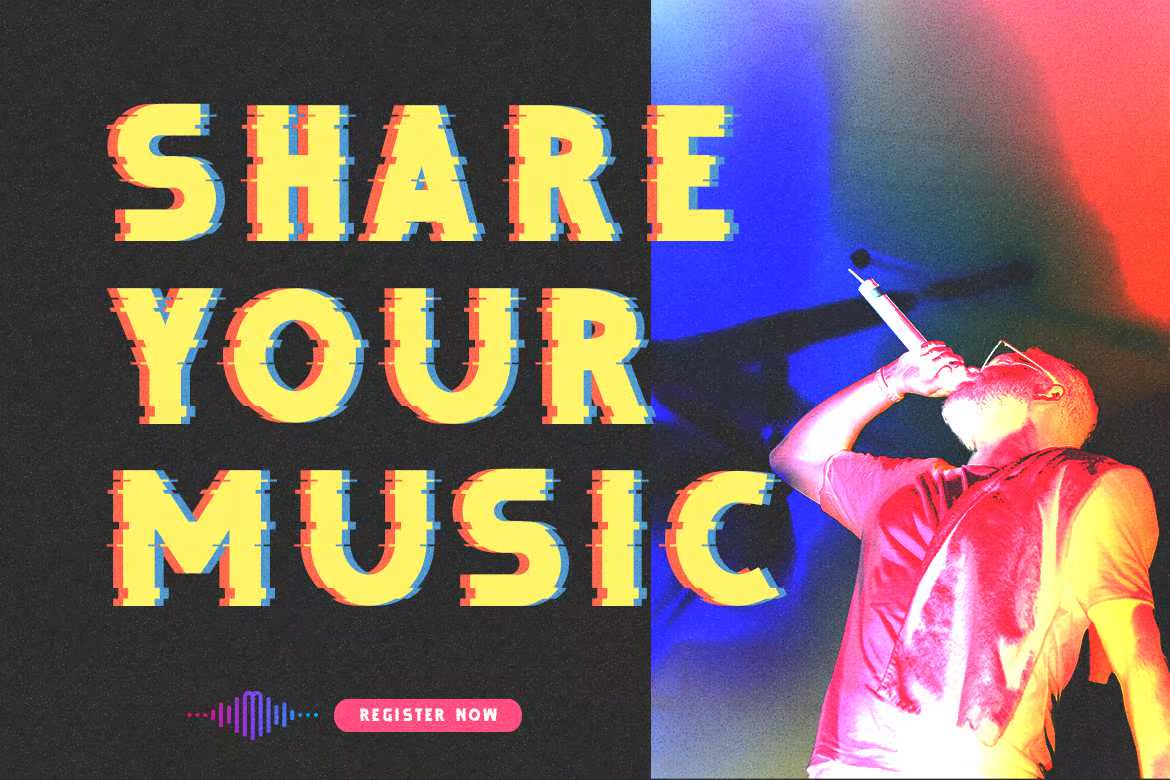
Debugge的所有功能都显示多语言字母、数字和标点符号。非常适合所有大小的标题行,以及具有最大和最小变化的区块软文本。无论是组织、电影、传单、帖子还是更多!FullVersionDownloadHere:Debugge是一个强大的全部功能,可显示多种语言的字母、数字和标点符号。非常适合所有大小的标题行,以及具有最大和最小变化的Block Softext。无论是组织、电影、传单、帖子还是其他内容!FullVersionDownloadHere: